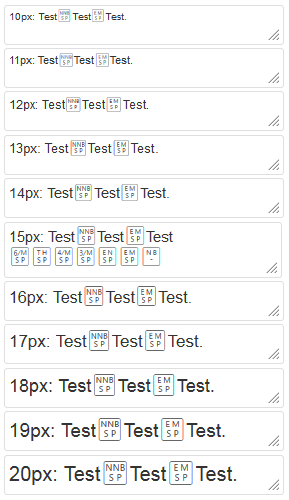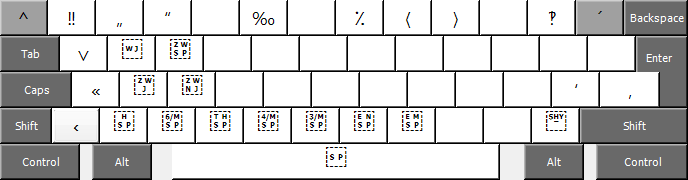
Name dieser „viereckigen“ Unicode-Repräsentation?
Ich muss mal ganz doow fragen, weil ich auch durchs Rumgoogeln grad gar keinen weitere Ansatzpunkt finde:
Gibt es einen Namen für die „viereckig“ Form, wie die (fehlenden) Unicode-Zeichen hier dargestellt werden?
Oder – ich weiß nicht, ob das ankommt – hier nochmal als Text: ㉅ ?
Kann man diese Art der „Platzhalter-Darstellung“ irgendwie auch bewusst erzwingen?
(Ich hätte speziell vor, das gern im Browser per Javascript zu tun.)
Supi, vielen Dank für die Anwort – ein Fallback-Font also …
(Sowas hab ich schon fast befürchtet; das macht mein eigentliches Vorhaben nun aller Voraussicht nach leider unmöglich. ^^)
Aber wenn wir schon mal drüber sind: gibts Alternativen zu dem genannten BMP-Fallback-Font? Mir gehts besonders um die Darstellung der „unsichtbaren“ Zeichen, wie Leerzeichen, etc. So à la:
Oder wie das unicode.org selber macht, in deren PDFs:
Nach etwas Hin und Her konnte ich herausfinden, dass der dortig verwendete Font für diese Darstellung wahrscheinlich „SpecialsUC5“ heißt. Kann das jemand bestätigen? Gibts den irgendwo? (Mein Google schweigt sich aus.)
Ein Fallback-Font wird doch erst dazu, wenn man ihn so einsetzt. Nichts hält dich davon ab, ihn als Primär-Font zu benutzen. Dann würden die Kästchen mit den Ziffern in jedem Fall erscheinen, genauso wie du es anscheinend willst.
Ich frage mich allerdings, ob ein Font hier überhaupt nötig ist. Wenn es darum geht, stur alle (oder bestimmte) Zeichen innerhalb eines HTML-Fragments anhand ihrer Unicodewerte darzustellen, lässt sich das doch einfach per JavaScript lösen. Mit ein bisschen CSS kannst du dann auch Kästchen um die Nummern ziehen.
Ich will vielleicht nochmal etwas genauer werden, dann klärt sich sicher auch das „Warum?“. ;)
Ich habe vor, in einem <input>-Feld oder einer <textarea> die darin eingegebenen „unsichtbaren“ (Sonder-)Zeichen eben doch anzuzeigen – während eben die normalen Buchstaben auch normal bleiben. Und hier ist eben nicht möglich, für jedes einzelne eingetippte Zeichen, nach einer Auswertung per JS, einen anderen Font anzugeben. Ich muss mir hier also etwas anderes einfallen lassen – weswegen eben mein ursprüngliches Vorhaben so nicht mehr möglich ist. ( … und auch CSS-Tricks hier nicht nützen; wir befinden uns quasi ein paar Ebenen „tiefer im Keller“. ;))
Ich hätte evtl. schon ’ne Idee … mal schauen.
Wer sonst noch Vorschläge hat: immer raus damit‼ ;)
Aber nochmal zurück zu diesem „SpecialUC5“-Font, bzw. Alternativen zum vorgeschlagenen BMP-Fallback-Font: gibts da nochwas gescheites irgendwo?
Also das ist auf jeden Fall möglich.
Entweder per JavaScript, wo für die entsprechenden Zeichen dann einfach auf den Fallback-Font umgeschaltet wird. Zum Beispiel indem sie einfach dynamisch mit einem SPAN-Tag umschlossen werden, dem eine alternative CSS-Klasse mit dem Fallback-Font zugewiesen wird.
Alternativ geht es auch rein als Fontlösung ohne JavaScript-Spielereien. Dazu müsstest du nur den entsprechenden Font bauen. Entweder nimmst du z.B. einen OpenSource-Font und baust statt der »unsichtbaren« Zeichen direkt die Fallback-Zeichen ein, oder du entfernst die entsprechenden Zeichen und der Fallback-Font greift dann über den Font Stack automatisch.
Zu Absatz 1 vllt. nochmal kurz:
Versteht mich doch mal, dass ich die Sache in einem <input> oder einer <textarea> machen möchte – dort kann ich doch nicht einen <span> aufmachen, wo eine andere Schrift benutzt wird. Das geht einfach nicht.
Wie dem auch sei, ich habe mir heute die Nacht um die Ohren geschlagen und mal die kleine Idee ausprobiert, welche so ziemlich genau die aus Absatz 2 ist: einen kleinen Font gebaut, wo die unsichtbaren Zeichen repräsentiert sind. Das klappt sogar auch eigentlich:
… aber eben auch nur „eigentlich“, weil:
Hat jemand eine Ahnung, warum es mir zwar so ziemlich alle Space-Zeichen „verspecialt“, nur den non-breaking space nicht? Ich hab den natürlich ganz normal wie alle anderen auch in meinem Font eingefügt. Aber für den greift scheinbar mein Font nicht, sondern es wird der nächste im Font-Stack benutzt. Was ist denn am NBSP so besonderes?
Sollte es etwas damit zu tun haben, dass der im U+0080, also weiter vorn im Latin-1 Supplement liegt, im Gegensatz zu allen anderen, die in der U+2000 General Punctuaton liegen? Das softhyphen zeigt es nämlich genauso nicht an.
Dagegen spricht, dass word joiner und zero-width space etc. aber auch nicht angezeigt (d.h. vom Special-Font repräsentiert) werden.
Mir leuchtet das alles jedenfalls grad nicht so richtig ein …
Ein Problem ist wohl, daß von den meisten Programmen Sonderzeichen auch besonders behandelt werden, d. h. ein Programm zeigt zum Beispiel einen Bindehemmer (ZWNJ) nicht unbedingt an, selbst wenn auf seiner Code-Stelle ein Zeichen liegt.
Vielleicht hilft es Dir: Die 16px-Rasterschrift „GNU Unifont“, welche ebenfalls die gesamte BMP abdeckt, hat auch eine Fassung, die solche Anzeigezeichen nur für Sonderzeichen hat, d. h. gewöhnliche Buchstaben sind normal enthalten.